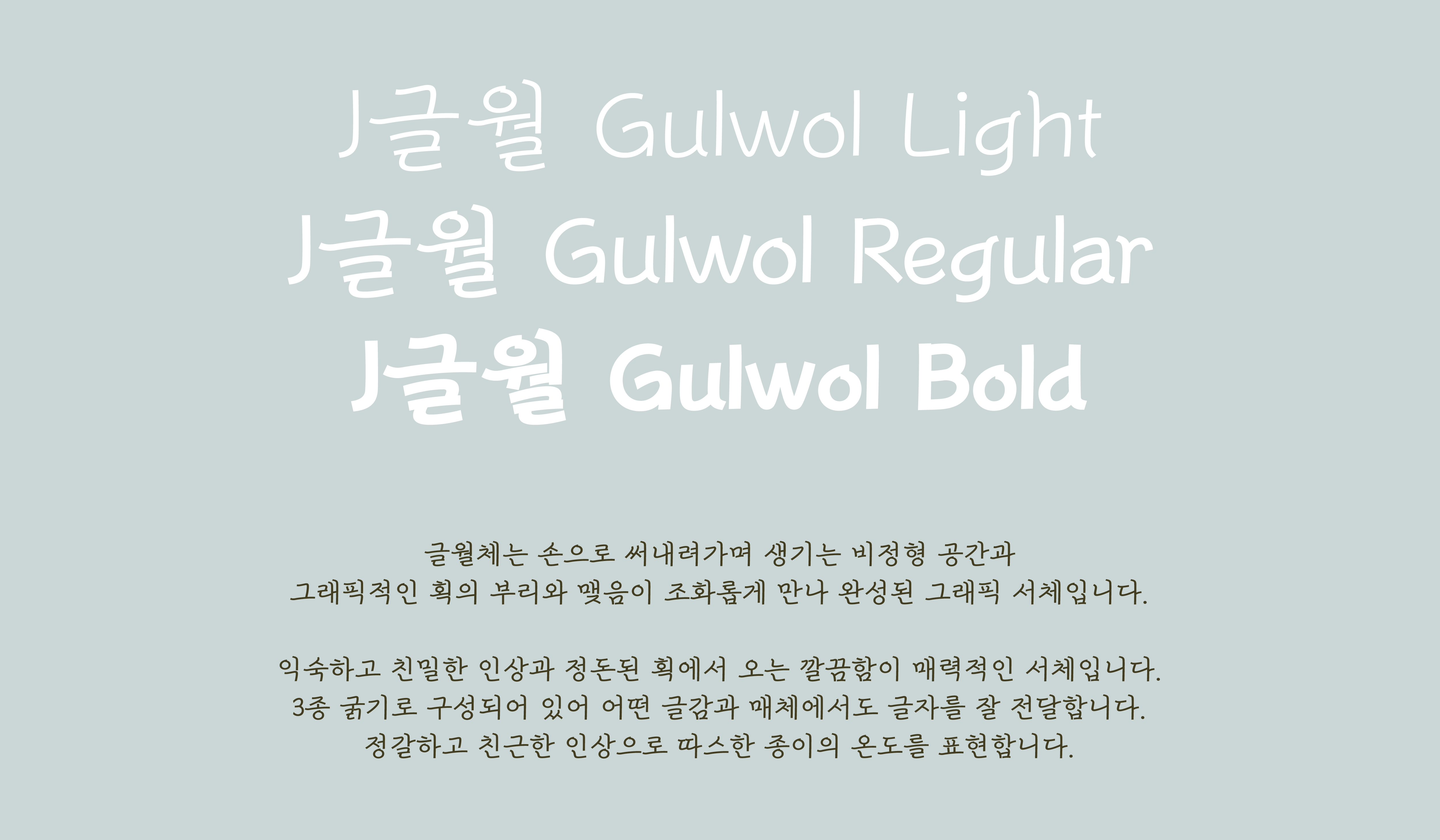
J글월
디자이너
곽보람
직지그래픽
다양한 컨셉으로 활용이 가능하고 독특한 디자인 요소가 많은 서체 시리즈. 개성있는 디테일로 시각적 재미를 더하고 풍부한 이야기를 담을 수 있는 서체이다.
글월체는 손으로 써내려가면서 생기는 비정형 공간이 주는 손맛과 그래픽적인 획의 시작(부리)과 맺음이 조화롭게 만나 완성된 그래픽체입니다. 익숙하고 친밀한 인상 그리고 정돈된 획에서 오는 깔끔함이 매력적인 서체이며 3종 굵기로 구성되어 있습니다. 어떤 매체에도, 어떤 콘텐츠에도 글월만의 정갈하고 친근한 인상으로 따뜻한 지면의 질감을 표현할 수 있습니다.